Kalau bosan dengan font yang terkesan formal, font whimsical bisa jadi pilihan yang lebih segar. Font whimsical adalah jenis font dengan desain unik, lucu, ceria, dan penuh imajinasi sehingga mampu memberikan kesan menyenangkan pada sebuah desain. Font ini banyak digunakan pada desain poster, logo, ilustrasi, kemasan produk, undangan, hingga desain yang bertema anak-anak.
15 Font Whimsical Gratis di Canva, Estetik dan Unik
- Canva menyediakan 15 font whimsical gratis dengan karakter unik, ceria, dekoratif, dan imajinatif untuk memberi kesan lebih segar pada desain.
- Pilihan font mencakup gaya tulisan tangan, kaligrafi, serif klasik, hingga nuansa Jepang dan retro; contohnya Pony Club, Railey, Glass Antiqua, serta Yuji Mai.
- Font-font ini cocok untuk judul, logo, poster, undangan, kemasan, kartu ucapan, dan konten media sosial; sejumlah font dekoratif kurang ideal untuk paragraf panjang atau teks kecil.
Di Canva, tersedia banyak pilihan font whimsical yang bisa digunakan pengguna secara gratis. Mulai dari gaya tulisan tangan, kaligrafi, hingga font dekoratif dengan karakter khas, yang dapat disesuaikan dengan kebutuhan desain. Berikut beberapa rekomendasi font whimsical gratis di Canva yang bisa digunakan untuk mempercantik desain dan layak masuk koleksi.
1. ITC Blackadder
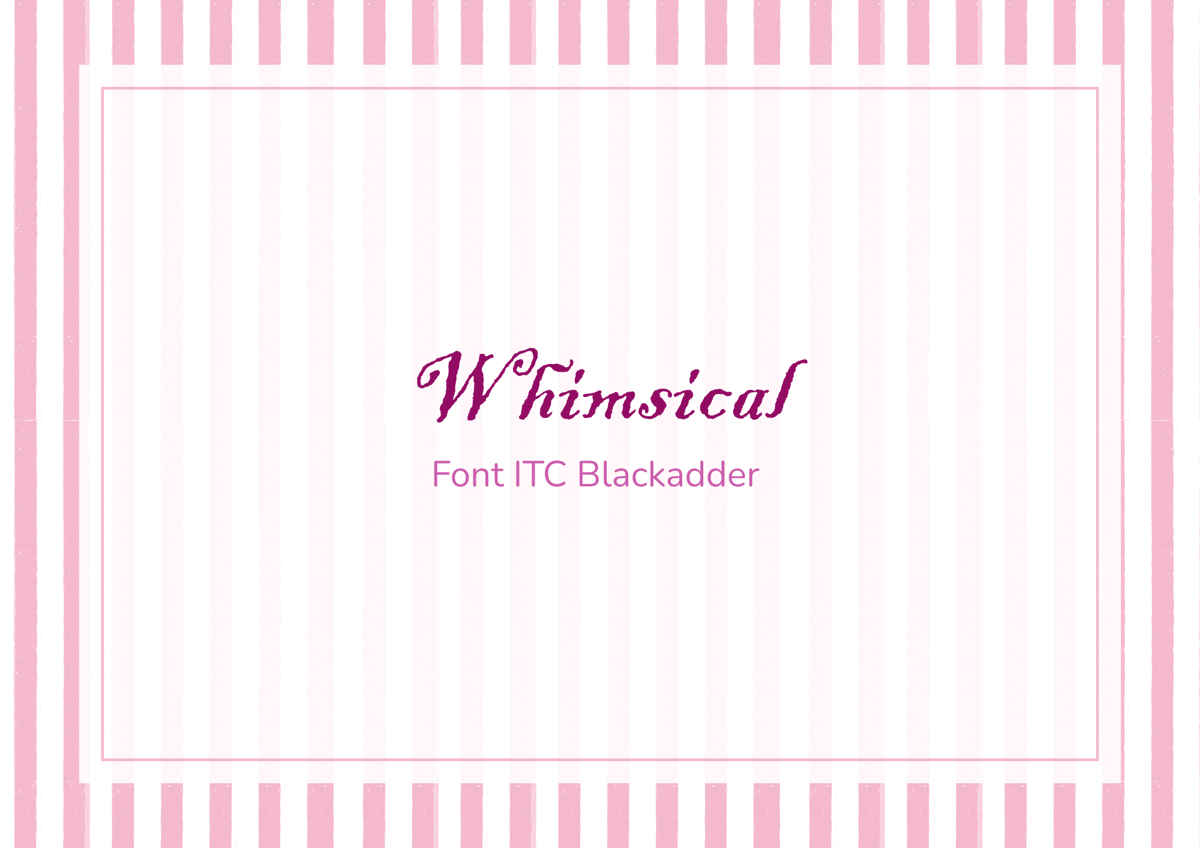
Ilustrasi font whimsical Canva (dok.pribadi/Dian Azizah) Butuh font yang elegan dan bergaya kaligrafi klasik? ITC Blackadder bisa jadi jawabannya. Font ini terinspirasi dari tulisan tangan dengan pena celup abad ke-16, sehingga gaya desainnya elegan dan menghadirkan kesan mewah, romantis, dan klasik. Font ini populer digunakan untuk undangan, poster, monogram, sertifikat, dan menu. Karena memberikan kesan dramatis dan artistik, font ini juga sangat cocok untuk keperluan teater. Namun, karena bentuk hurufnya yang dekoratif, font ini kurang cocok digunakan untuk paragraf panjang karena tingkat keterbacaannya relatif rendah.
2. Black and White Picture
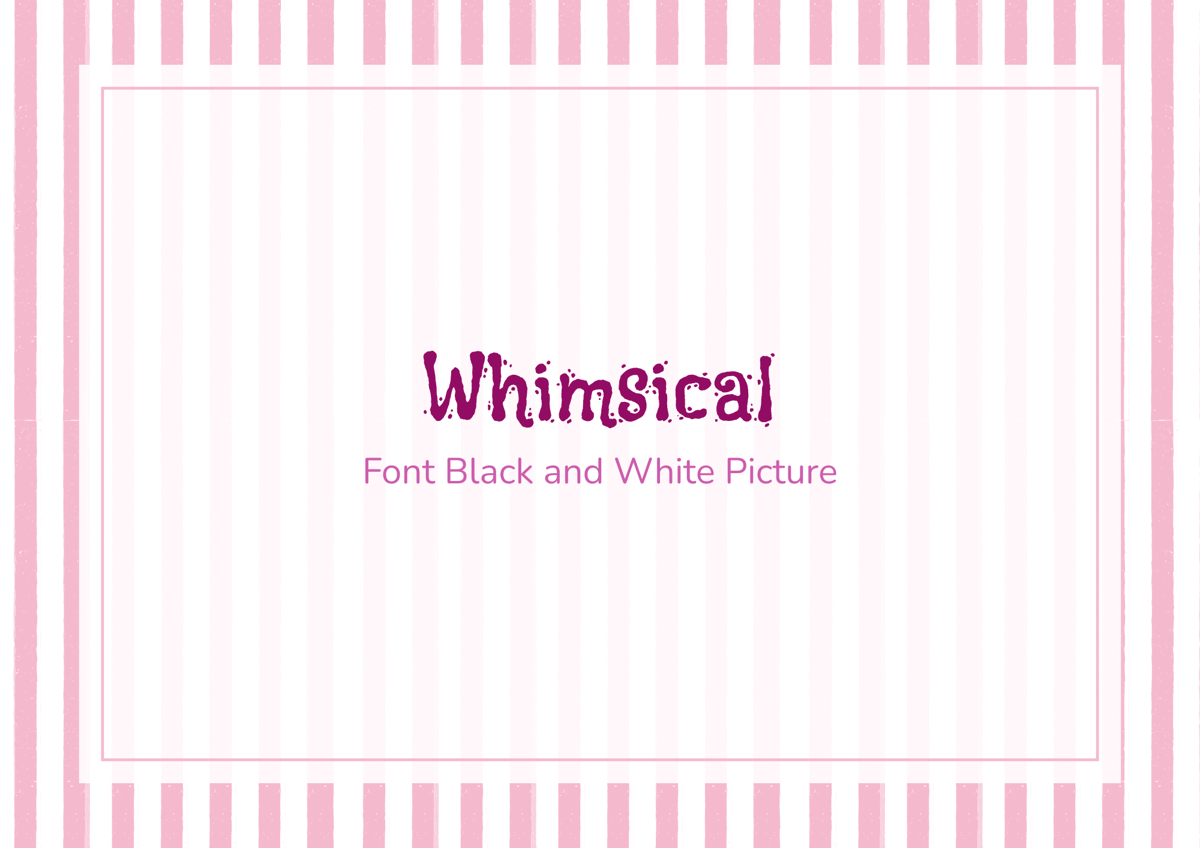
Ilustrasi font whimsical Canva (dok.pribadi/Dian Azizah) Font Black and White Picture adalah jenis font yang mendukung huruf Korea (Hangul) dan Latin yang ekspresif dan memberikan nuansa nostalgia hitam putih yang pudar melalui tekstur kasar (scratchy) dan bergaris-garis, sehingga memberikan nuansa vintage, playful, dan artistik. Font ini cocok untuk digunakan untuk poster, judul, ilustrasi, kemasan, kartu ucapan, hingga desain bertema retro dan anak-anak. Namun, karena bentuk hurufnya yang dekoratif dan tidak beraturan, Black and White Picture kurang cocok untuk paragraf panjang dan teks berukuran kecil.
3. Pony Club
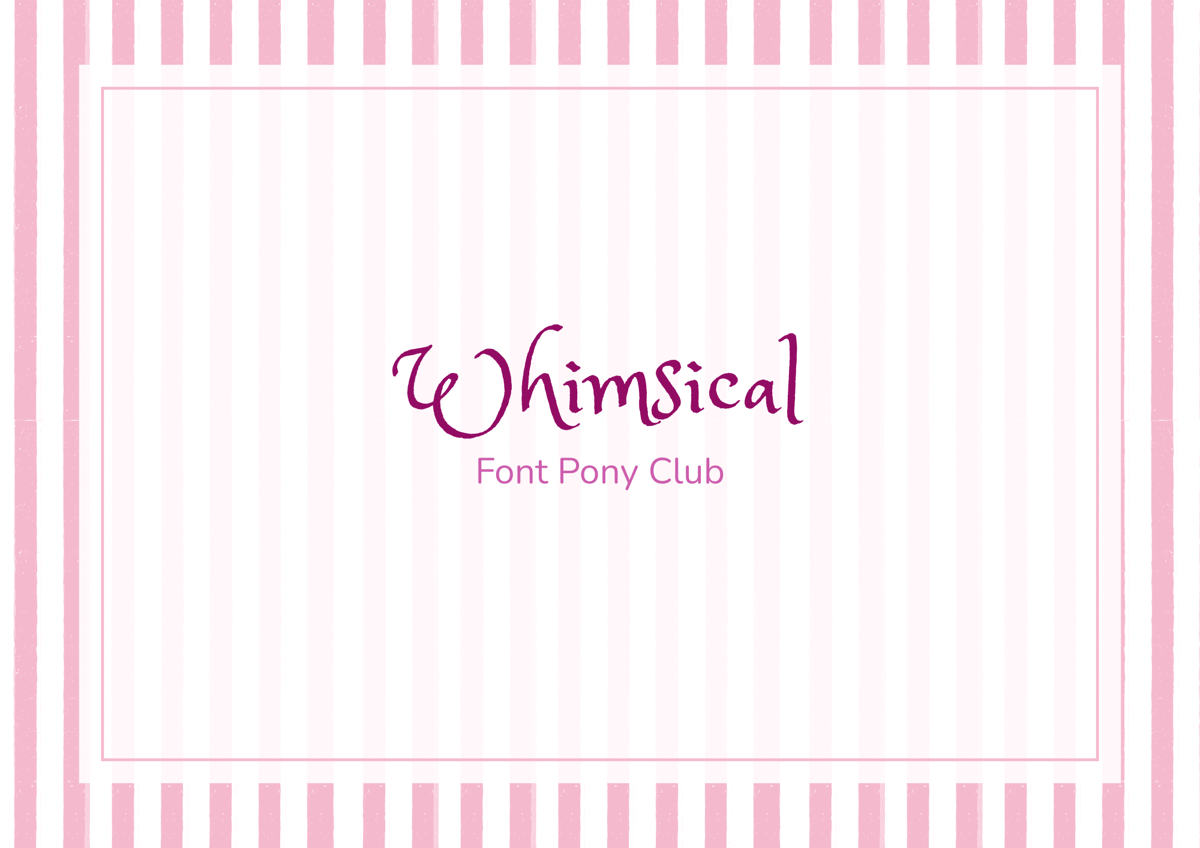
Ilustrasi font whimsical Canva (dok.pribadi/Dian Azizah) Kalau kamu lagi cari font yang terlihat lucu, ceria, dan penuh imajinasi, Pony Club bisa jadi pilihan yang tepat. Font Pony Club adalah font dengan gaya tulisan tangan (handwritten) yang memiliki bentuk huruf membulat, sedikit tidak beraturan seperti coretan anak-anak, dan memberikan kesan ramah, dan playful. Font ini cocok untuk desain bertema anak-anak, poster, logo, kartu ucapan, undangan ulang tahun, scrapbook, hingga konten media sosial. Namun, karena tampilannya yang cukup dekoratif, font ini lebih cocok digunakan sebagai judul atau teks pendek daripada paragraf panjang agar mudah dibaca.
4. Railey
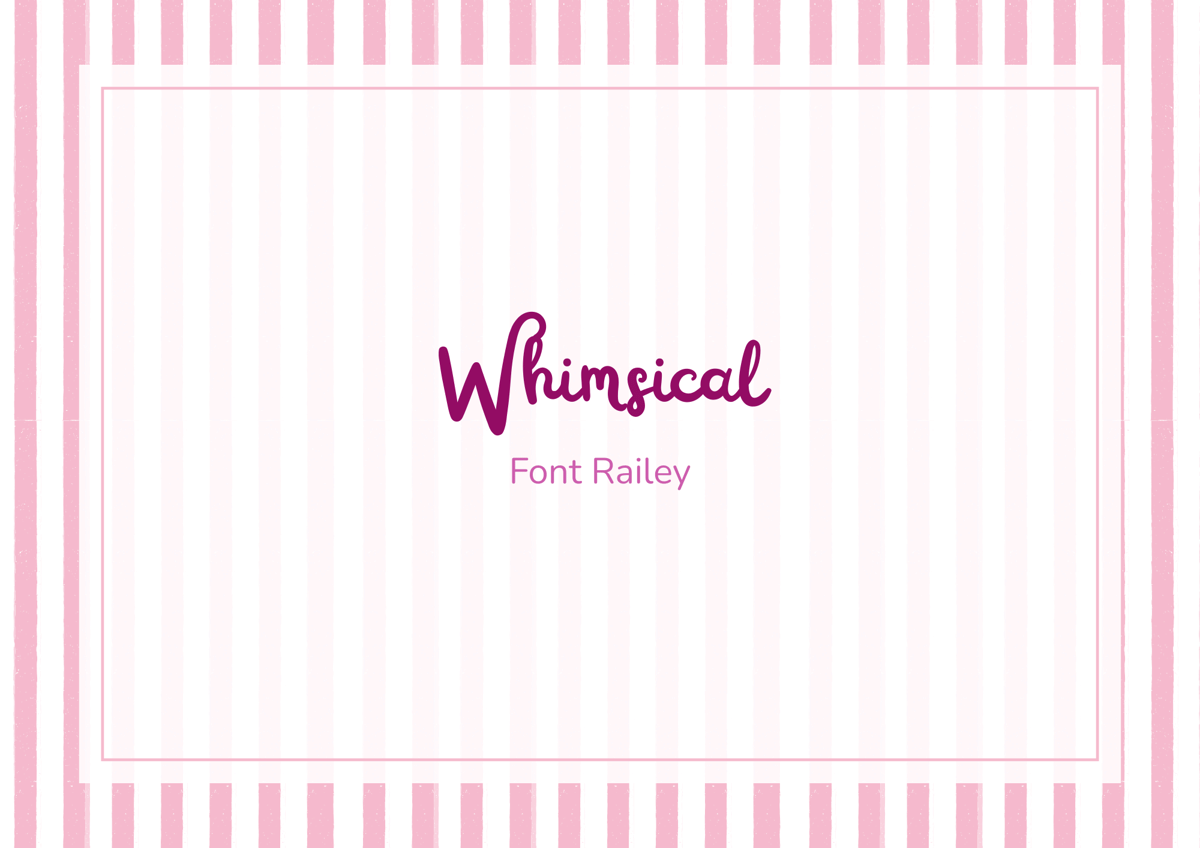
Ilustrasi font whimsical Canva (dok.pribadi/Dian Azizah) Font Railey adalah font dengan gaya tulisan tangan (handwritten) yang memiliki goresan yang halus, mengalir, dan dihiasi sapuan huruf yang dekoratif sehingga memberikan kesan hangat, feminin, dan personal. Font ini cocok digunakan untuk logo, undangan, kemasan produk, kartu ucapan, dan kutipan inspiratif (quotes).
5. Crafty Girls
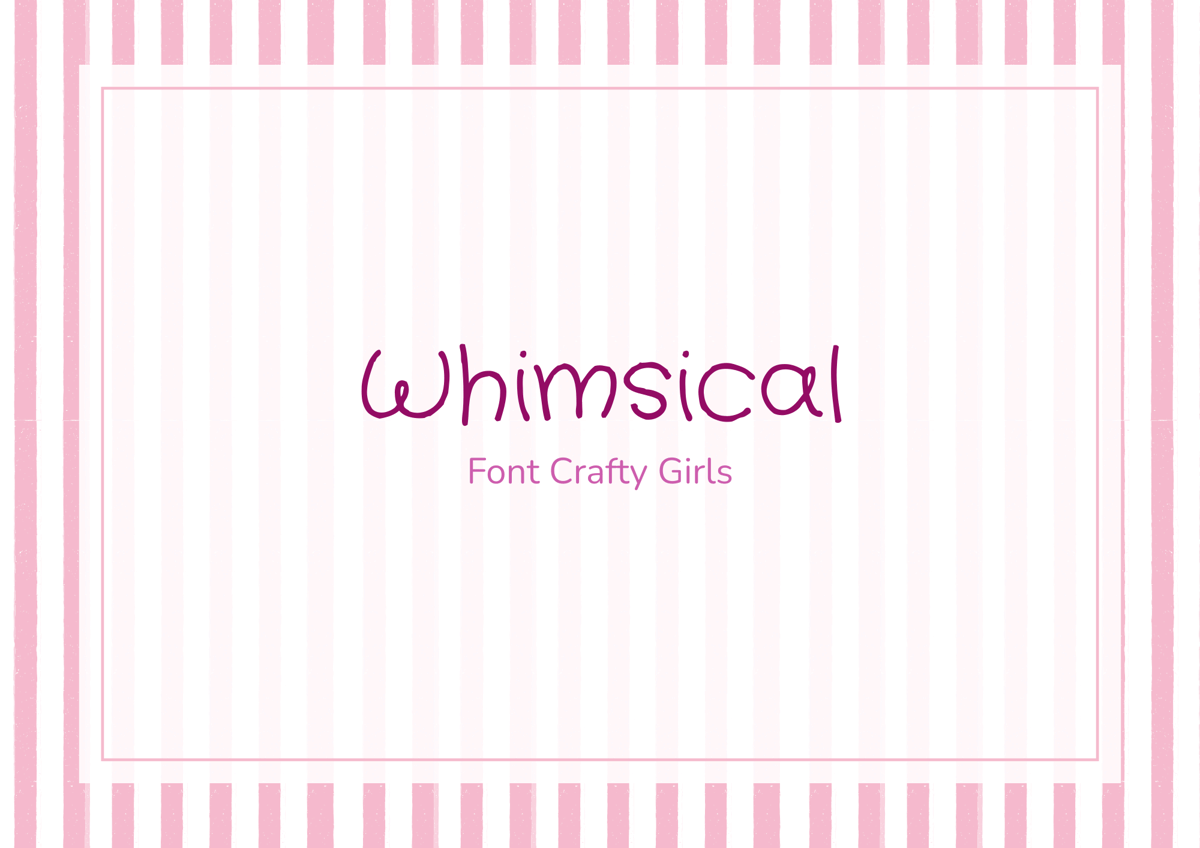
Ilustrasi font whimsical Canva (dok.pribadi/Dian Azizah) Kalau kamu lagi nyari font yang lucu dan terlihat seperti tulisan tangan anak-anak, Crafty Girls bisa menjadi pilihan yang tepat. Font satu ini memiliki bentuk huruf yang membulat, sedikit tidak beraturan, dan memberikan kesan ceria dan kreatif. Tampilannya sederhana sehingga font ini cocok untuk worksheet, poster, kartu ucapan, scrapbook, logo, hingga desain bertema anak-anak. Meskipun lebih mudah dibaca dibandingkan dengan font lainnya, Crafty Girls lebih ideal digunakan untuk judul atau teks pendek dibandingkan dengan paragraf panjang agar desain tetap terlihat menarik.
6. Hangout
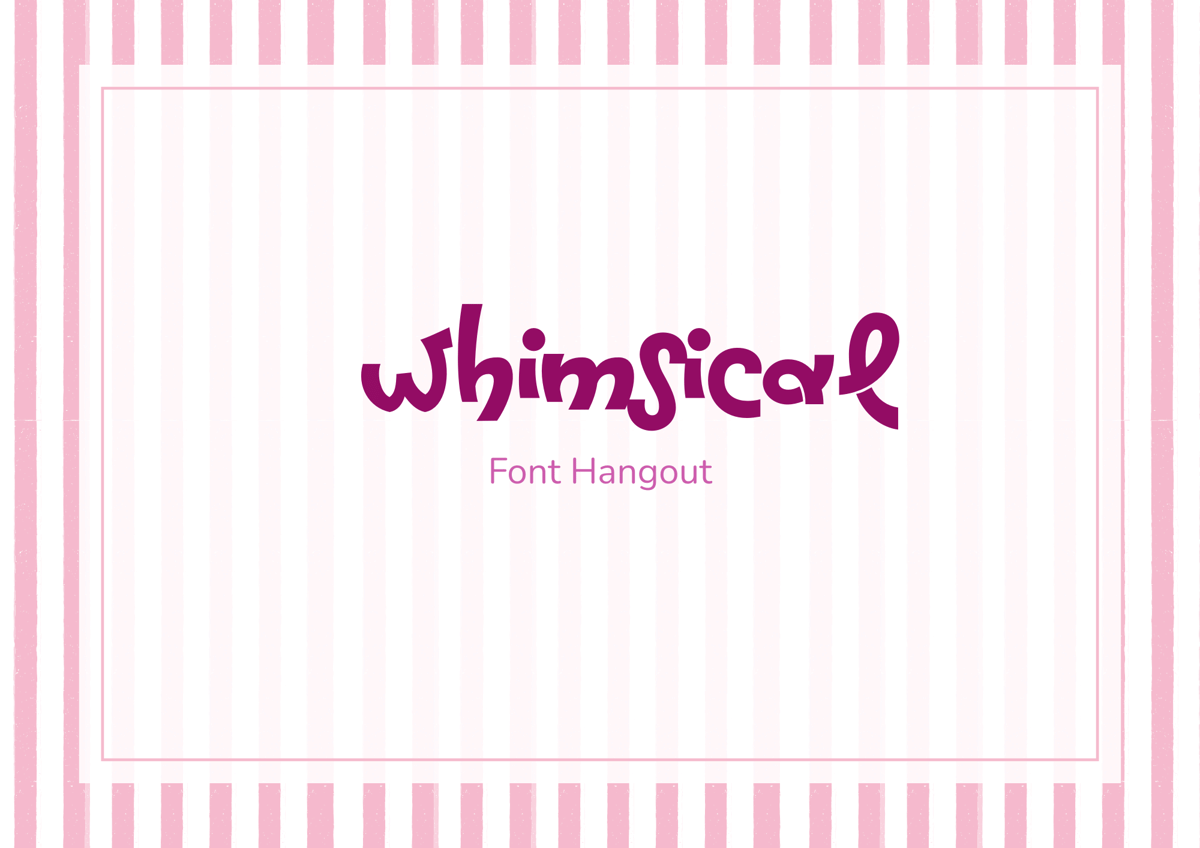
Ilustrasi font whimsical Canva (dok.pribadi/Dian Azizah) Font Hangout memiliki bentuk huruf yang membulat dengan gaya tulisan tangan yang playful sehingga memberikan kesan santai, ramah, menyenangkan, dan penuh karakter. Font ini sangat pas sebagai judul atau elemen dekoratif pada poster, konten media sosial, kemasan produk, maupun desain bertema anak-anak.
7. Sweet Dreams
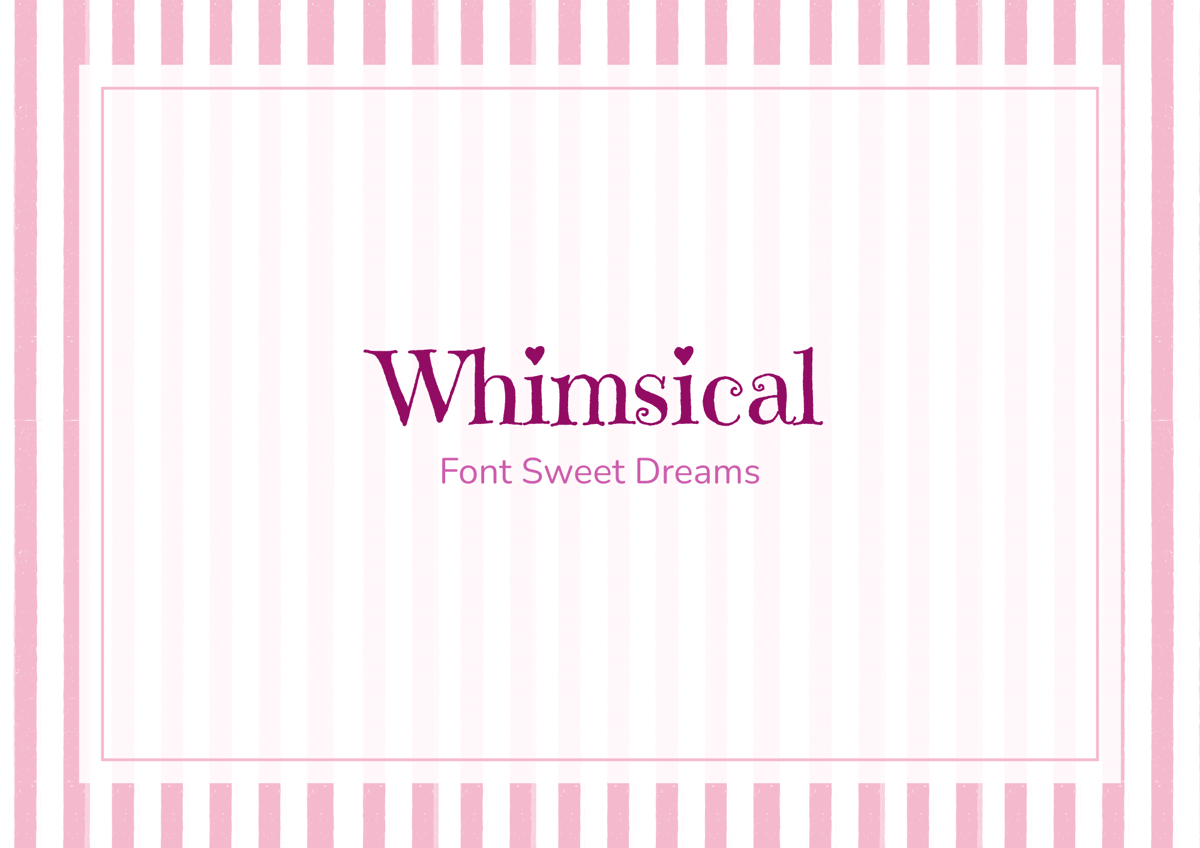
Ilustrasi font whimsical Canva (dok.pribadi/Dian Azizah) Mau buat desain yang kelihatan manis dan menggemaskan? Font Sweet Dreams bisa menjadi pilihan yang tepat. Font ini memiliki huruf yang membulat dan gaya tulisan tangan yang lembut sehingga memberikan kesan hangat dan ceria. Sweet Dreams cocok digunakan untuk judul, logo, atau elemen dekoratif pada desain bertema anak-anak, makanan manis, kerajinan tangan, maupun konten media sosial.
8. Glass Antiqua
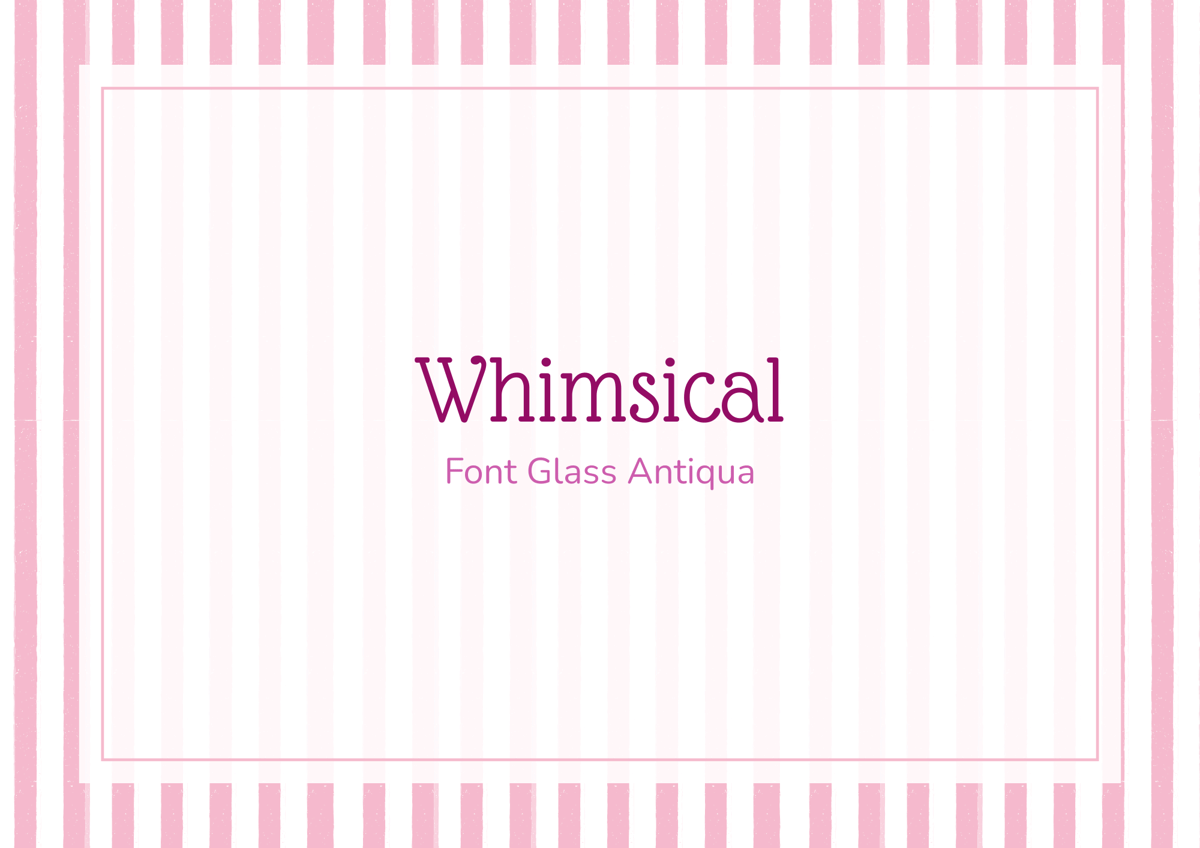
Ilustrasi font whimsical Canva (dok.pribadi/Dian Azizah) Font Glass Antiqua adalah font serif bernuansa klasik dan vintage tanpa terlihat terlalu formal. Terinspirasi oleh tipografi Romawi Kuno, font ini menonjolkan lekukan lembut bergaya Art Nouveau serta elemen-elemen kursif. Bentuk hurufnya yang unik membuat font ini cocok digunakan sebagai judul, logo, atau elemen dekoratif untuk membuat desain terlihat lebih berkarakter dan berkesan. Glass Antiqua juga sangat cocok untuk menambahkan nuansa hangat, nostalgia, atau holistik pada desain.
9. Distillery Display
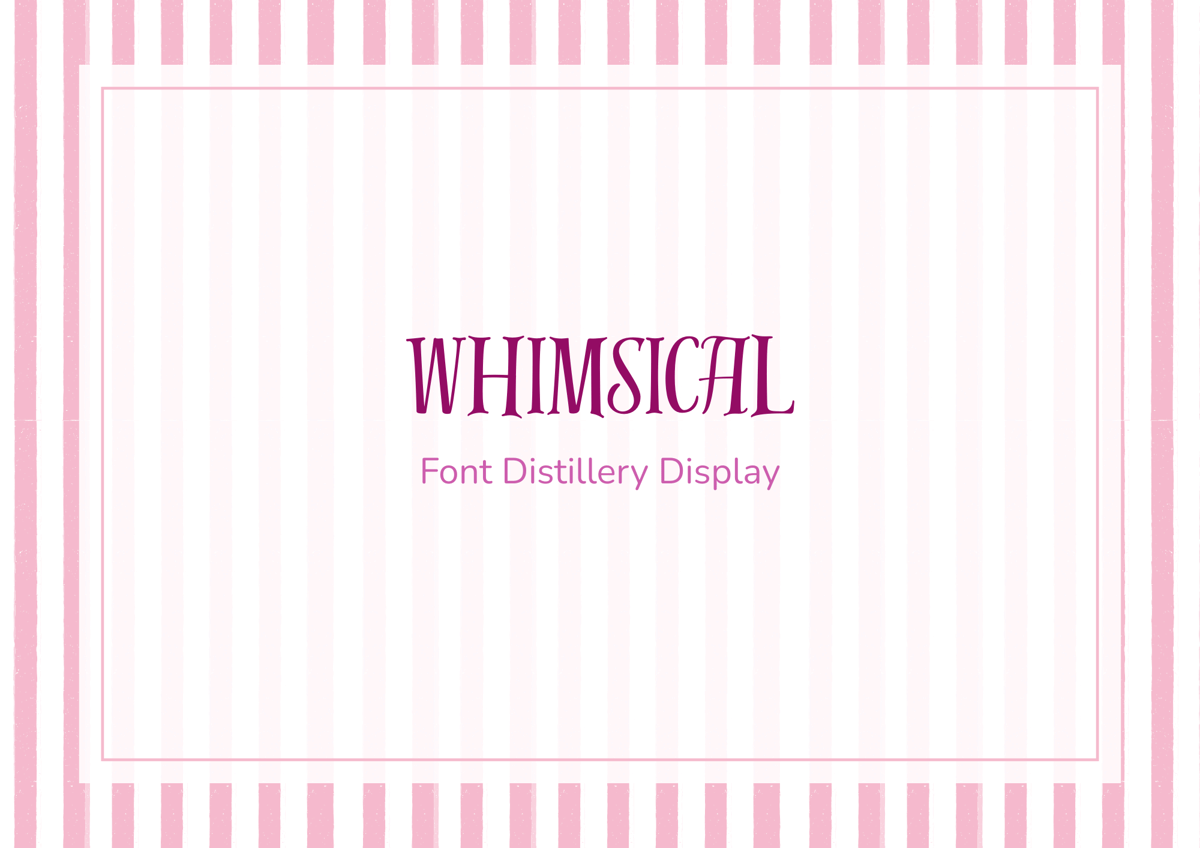
ilustrasi font whimsical Canva (dok. pribadi/Dian Azizah) Distillery Display adalah font serif yang berani dan membuat desain akan terlihat klasik sekaligus berkelas. Font ini memiliki bentuk yang menonjolkan lekukan yang tegas dan kontras tinggi dengan sentuhan vintage sehingga memberikan kesan elegan, mewah, dan artistik. Distillery Display ideal digunakan sebagai judul, logo, atau elemen dekoratif pada kemasan, poster, maupun branding agar desain terlihat lebih eksklusif dan menarik perhatian.
10. Awesome Latchusca
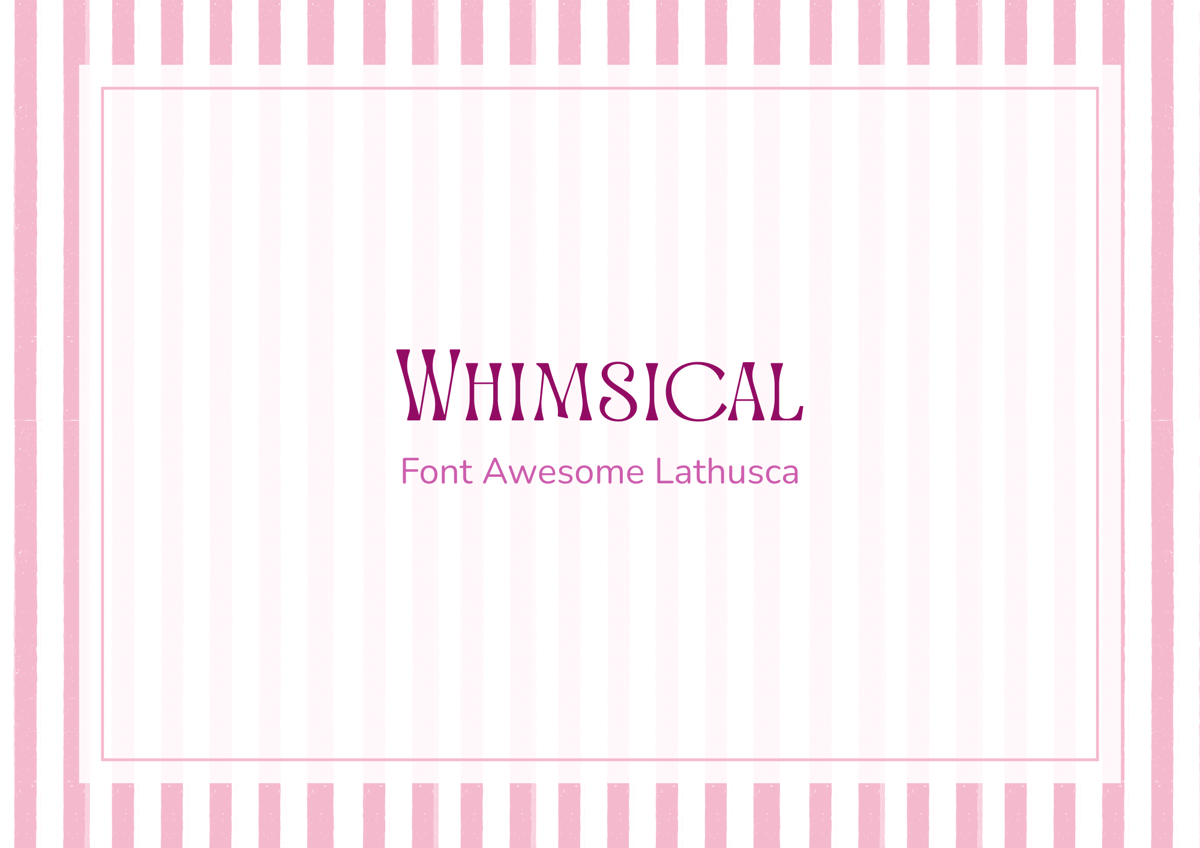
Ilustrasi font whimsical Canva (dok. pribadi/Dian Azizah) Kalau kamu ingin membuat desain yang terlihat ceria dan penuh karakter, Awesome Lathusca bisa menjadi pilihan yang tepat. Font bergaya tulisan tangan ini memiliki goresan yang tebal, membulat, dan sedikit tidak beraturan sehingga memberikan kesan santai, hangat, dan playful. Karena memiliki bentuk huruf yang unik, font ini cocok digunakan sebagai judul atau elemen dekoratif pada poster, logo, kemasan produk, kartu ucapan, hingga konten media sosial dengan tema yang ceria dan penuh karakter.
11. Yuji Mai
Ilustrasi font whimsical Canva (dok. pribadi/Dian Azizah) Font Yuji Mai adalah font bergaya kaligrafi yang terinspirasi dari tulisan tangan tradisional Jepang dengan sapuan garis yang halus dan dekoratif sehingga dapat menghadirkan nuansa Jepang yang elegan dan artistik pada desain. Meskipun mendukung huruf Latin, karakter font tetap mempertahankan estetika khas kaligrafi Jepang sehingga cocok digunakan untuk poster, logo, kemasan, menu, undangan, hingga desain bertema budaya Asia.
12. Meow Script
Ilustrasi font whimsical Canva (dok. pribadi/Dian Azizah) Meow Script adalah font bergaya tulisan tangan yang memiliki goresan yang halus, mengalir, dan sedikit dekoratif sehingga menghadirkan kesan hangat, anggun, dan modern. Penggunaan font ini juga memberikan sentuhan elegan sekaligus personal pada desain. Meow Script cocok digunakan sebagai judul, logo, atau elemen dekoratif pada undangan, kartu ucapan, kemasan produk, dan kutipan. Selain itu, font ini juga dapat digunakan pada desain bertema romantis dan feminin.
13. Sugar Pie
Ilustrasi font whimsical Canva (dok. pribadi/Dian Azizah) Sugar Pie adalah font bergaya tulisan tangan yang memiliki bentuk huruf yang membulat, lembut, dan sedikit dekoratif sehingga menghadirkan kesan ceria, hangat, dan playful. Karena dapat memberikan kesan yang manis dan menggemaskan pada desain, font ini cocok untuk poster, logo, kemasan makanan atau minuman, stiker, hingga desain bertema anak-anak.
14. Moonlight
Ilustrasi font whimsical Canva (dok. pribadi/Dian Azizah) Moonlight bisa menjadi pilihan yang menarik jika kamu ingin memberikan sentuhan elegan dan romantis pada desain. Font bergaya tulisan tangan ini memiliki goresan yang halus, mengalir, dan dihiasi lengkungan yang anggun sehingga menghadirkan kesan mewah, feminin, dan premium tanpa mengurangi kesan hangat dan personal. Font ini cocok digunakan untuk logo, undangan, kartu ucapan, kemasan produk, hingga quotes.
15. Anaktoria
Ilustrasi font whimsical Canva (dok. pribadi/Dian Azizah) Font Anoktaria bisa menjadi pilihan yang tepat kalau kamu ingin menghadirkan suasana klasik yang elegan pada desain. Font bergaya serif ini memiliki bentuk huruf yang ramping dengan sentuhan khas tipografi klasik sehingga memberikan kesan mewah, artistik, dan berkelas. Font ini sangat efektif sebagai judul, logo, atau elemen dekoratif pada poster, undangan, maupun kemasan agar desain terlihat lebih eksklusif dan berkarakter.
Beberapa font whimsical gratis di Canva bisa membantumu dalam menemukan desain huruf yang sesuai kebutuhan. Dari 15 rekomendasi font di atas, mana yang ingin kamu coba, nih?